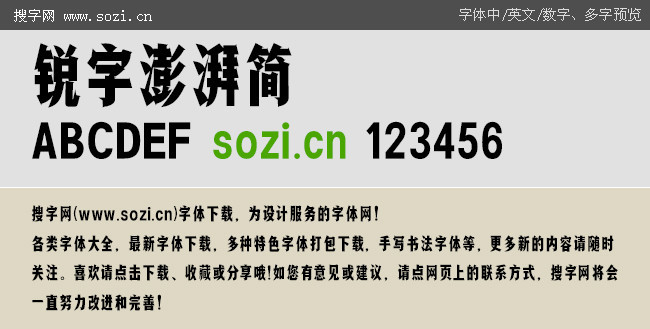
銳字澎湃簡
搜字網(wǎng)提供一款銳字澎湃簡中文字體下載,銳字澎湃簡是一款實用性強的常規(guī)字體,筆畫粗黑,字型飽滿,氣勢雄健,適合用于報刊標(biāo)頭設(shè)計,包裝設(shè)計,海報設(shè)計等廣告應(yīng)用。(此款為個人非商用版,如需商用請聯(lián)系銳字工房購買)